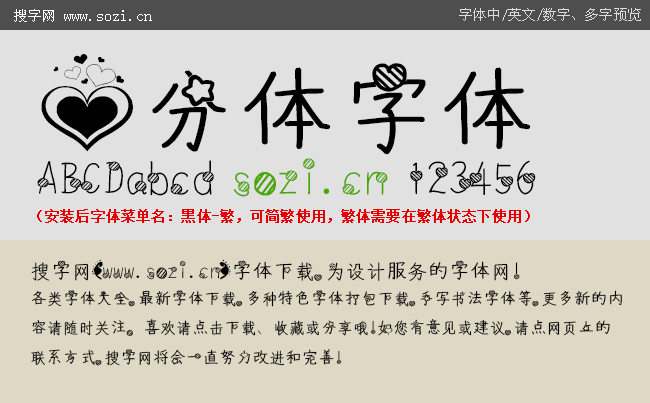
心分體字體
搜字網(wǎng)給大家提供一款卡通手寫(xiě)風(fēng)格的手機(jī)中文字體下載。修改者將它命名為心分體字體,這款手機(jī)字體是仿照兒童手寫(xiě)風(fēng)格的卡通手寫(xiě)字體,結(jié)構(gòu)帶有POP字體風(fēng)格,字體的一些筆畫(huà)還替換成了有趣卡通的心形和星形圖案,特別適合喜歡手機(jī)字體個(gè)性一些的朋友在手機(jī)上安裝使用。